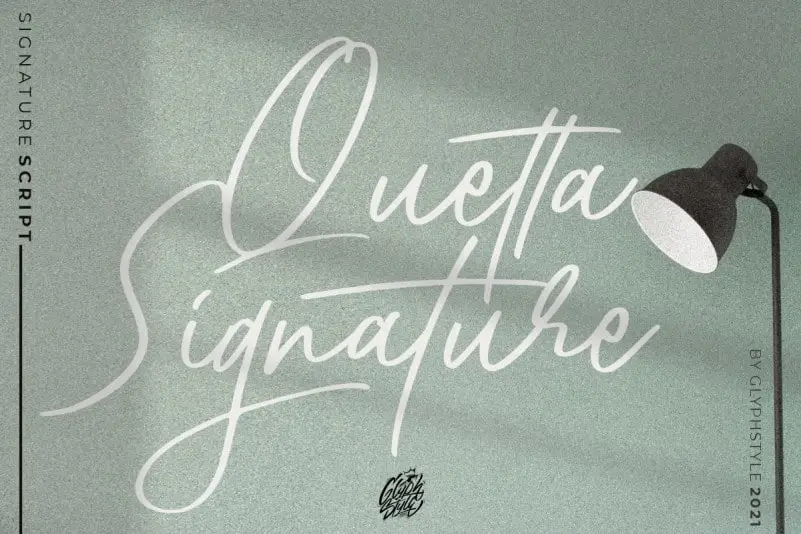
Quetta Signature Script Font – Download Grátis
A Quetta Signature Script Font é uma fonte casual que transmite elegância e sofisticação com sua linha natural e fluida. Essa opção perfeita para aplicações variadas, incluindo coberturas, marcações, identidades de negócios, logotipos, rótulos de produto, cartões de visita e até mesmo nomes, oferece uma expressão autêntica que torna qualquer projeto mais atraente. Criada por GlyphStyle, essa fonte foi projetada para ser um recurso versátil em sua gama de handwrited fonts, permitindo-lhe experimentar seu próprio estilo e personalização sem comprometer o design elegante e sofisticado que ela proporciona.